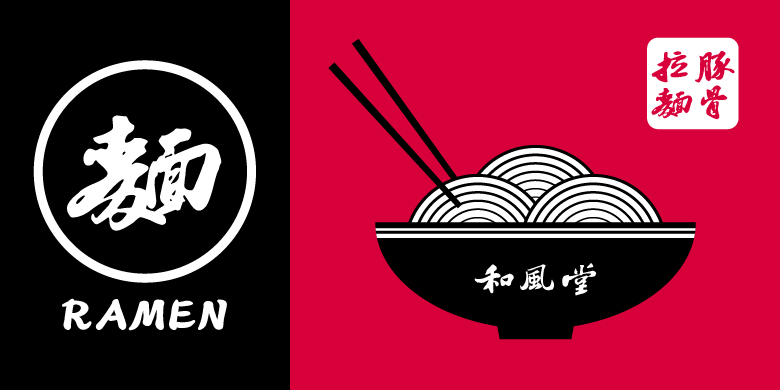
书体坊苏轼行书
品牌: 书体坊
设计师: 禚效锋
分类:常规书写·毛笔
书体坊苏轼行书,以苏轼流传后世的书法作品为字源,以《洞庭春色赋》《中山松醪赋》《赤壁赋》《归去来兮辞》《寒食贴上》《西山诗帖》等作品字形为基本,集字制作而成。字体在结字上,突出苏轼书法的主要特征,结字扁平,撇捺笔画舒展,横轻竖重,轻重错落;在用墨上,丰腴肥美,字字丰润,妩媚娟秀,朴拙厚重,平和中正。字体风格整体统一,体现了苏轼书法的主要风貌。
禚效锋,江苏省邳州市人,书法教师,历时多年,精选最有时代风格、最有代表性的书法作品,开发出书体坊系列书法字体近百种,深受大家喜爱。